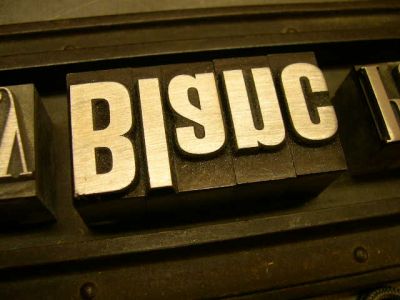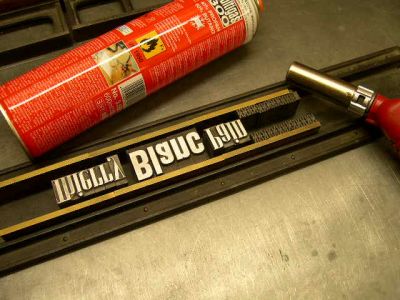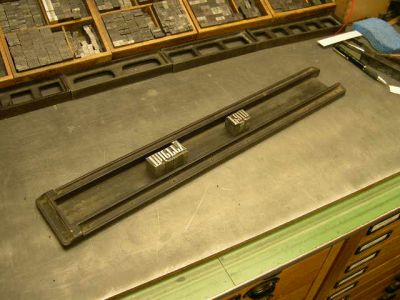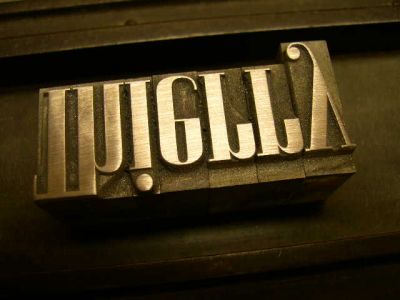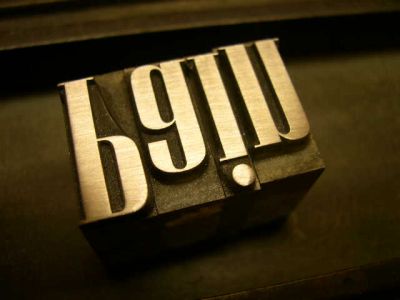
Neue Collage: "Schmerz" oder "Gott hat ihn un
Die Initialzündung zum Bau einer neuen Collage besteht bei mir immer aus einem Begriff, einem Wort oder einer Emotion, die ich auffange, festhalte und assoziiere.
In diesem Fall diente mir Kollege Thierry Blancpain als Zündfunke.
Und daß, ohne davon zu wissen. Ich schätze Thierry als einen Fachkollegen aus der Schweiz, mit dem ich mich hier gerne im Kreise anderer Kollegen austausche. Näheren Kontakt hatten wir nie. Das war auch nicht nötig, sein Name reichte völlig.
Blancpain - Schmerz in seiner reinsten Form.
Grundsätzlich ist Schmerz etwas sehr sinnvolles und ohne ihn könnten wir wahrscheinlich nicht einmal überleben. In idealisierter Form finden wir den Reinen Schmerz in vielen Religionen, auch in der Hl. Katholischen Kirche, die sich seiner in der Zeit der Inquisition bediente. (Bitte jetzt nicht nach "political correctness" rufen, ja.)
Schmerz ist ursprünglich und direkt. Steht nicht zur Diskussion, läßt sich nicht ignorieren und auch nicht relativieren. Neben den körperlichen Schmerzen gibt es viel ärgere seelische Schmerzen. Beim Verlust eines lieben Mitmenschen oder auch beim Verlassenwerden durch einen solchen. Wobei das oft identisch ist.
Das war Grundlage meiner theoretischen Überlegungen zur Collage.
Nun steht fest: Ich baue sie.
Name:
"Schmerz" oder "Gott hat ihn uns gegeben".
Auch bei der Namenssuche gilt wieder das Prinzip der Polarisierung.
Format: 535 mm x 90 mm
Gewicht: ca. 8 kg
Bestandteile:
72 p Corvinus halbfett
84 p Bücher-Grotesk (kein Schriftmuster vorhanden)
Ein Satzschiff für Spaltenkolumnen aus der Akzidenzabteilung einer Zeitungssetzerei der 60er Jahre.
Diverse andere Bauteile, die sich im Laufe der nächsten Wochen ergeben werden.
Fertig: Dezember 2006
Bleisetzer
Die untere rechte Aufnahme gefällt mir sehr gut.
georg, ist das eigentlich eine Th-ligatur?
Gut erkannt, Kollege.
Ja, die Corvinus hat eine Th-Ligatur, schon was seltenes.
Irgendwann schrieb hier ein Kollege in Bezug auf die Schrift Reporter, er wäre regelrecht neidisch, weil die Bleisatz-Reporter viel mehr Ligaturen aufzeigen würde als die digitalisierten Fonts. Woran mag das liegen? Es dürfte doch vom Arbeitsaufwand her leichter sein, eine Ligatur zu digitalisieren als eine Bleisatz-Ligatur herzustellen:
Dieser Collagen-Bau ist als Fortsetzungsroman gedacht. Ich werde über die weitere Entwicklung berichten.
- Eine 84 p Bücher-Grotesk
- Messinglinien
- Schmuck-Vignetten aus Blei
Das Füllmaterial, also Regletten und Hohlstege, wird vermutlich nicht geputzt, damit es die schwarze Patine behält.
Was der Lötkolben auf dem Bild soll?
Nun, Blei hat seinen Schmelzpunkt bei 330° Celsius.
Der Schmelzpunkt von Eisen (das Satzschiff) liegt bei rd. 1.500° Celsius, der von Messing bei etwa 900° Celsius.
Feuer ist ja reinigend, wenn auch schmerzhaft. Also reiner Schmerz.
Daraus läßt sich nun einiges ableiten :-)